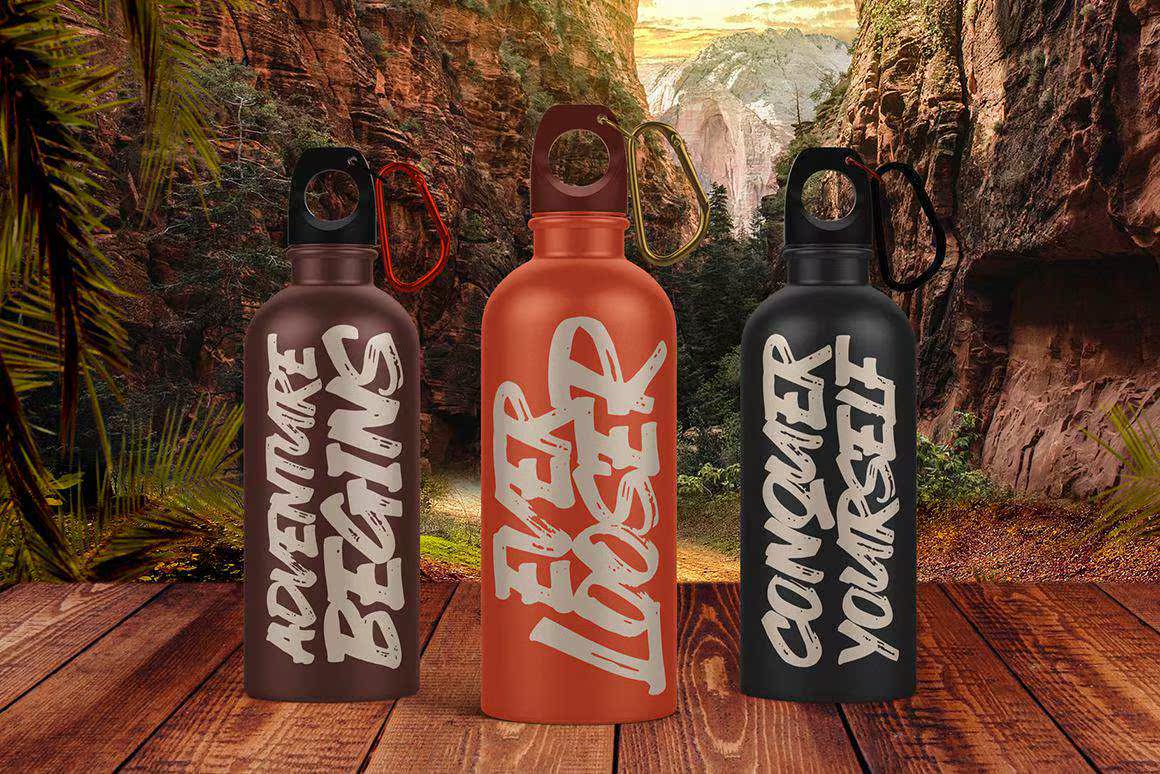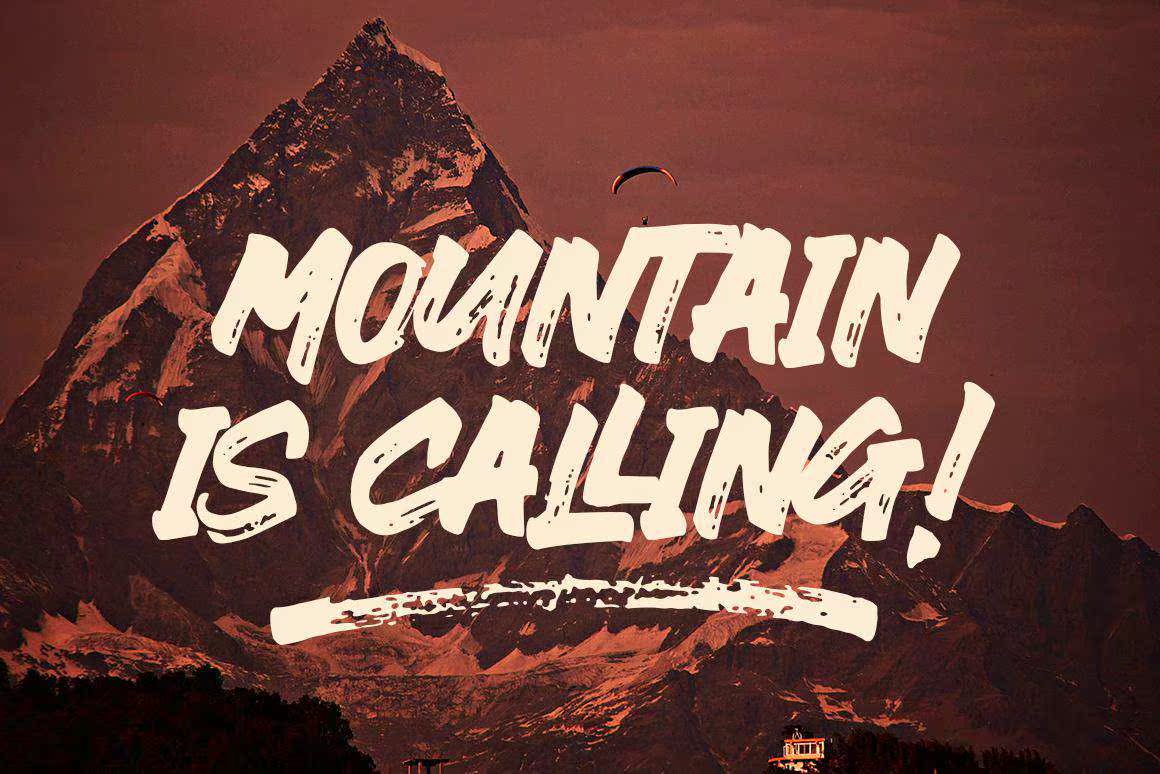
永远放松!一个具有特定纹理的隐藏式RushFont。此Font使每个角色的组合更加完美。您可以通过混合和匹配来输入UniqueCombing。它可以用于您的所有项目需要。每个页面都有自己的唯一消息,并且在与其他页面会面时都会提供动态和令人愉悦的接近度。此Font可以在任何时间和任何项目中使用。您可以在演示图中看到除此之外,EVERLOOSERlooks在设计项目上“狂野”。展示EVERLOOSER!一个具有特定纹理的隐藏式RushFont。此Font使每个角色的组合更加完美。您可以通过混合和匹配来输入UniqueCombing。它可以用于您的所有项目需要。每个页面都有自己的唯一消息,并且在与其他页面会面时都会提供动态和令人愉悦的接近度。此Font可以在任何时间和任何项目中使用。您可以在演示图中看到除此之外,EVERLOOSERlooks在设计项目中表现出“野性”。